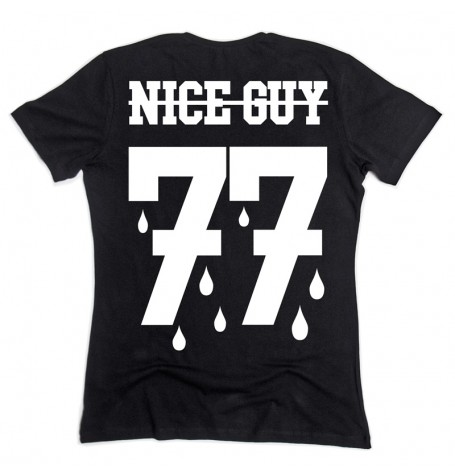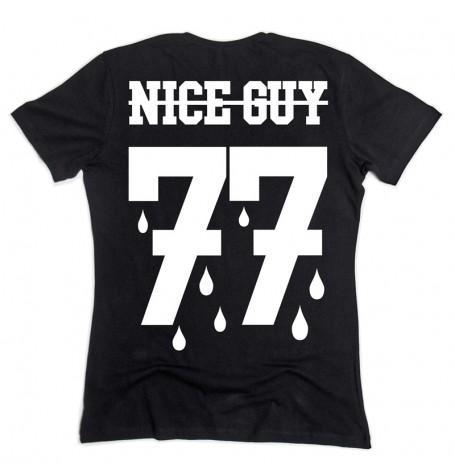
Welche Schrift ist das ?
Suche seit tagen den Font Nice Guy 77. Finde es aber nicht kann mir einer helfen ? :/
Ich glaube, Robert hat sie gefunden. Die Erstgenannte passt auffallend gut, nur E und G scheinen in der Mitte modifiziert (wegen der Durchstreichung?). Und die Sieben. Vielleicht wurde noch eine zusätzliche Kontur bzw. Versatz verwendet, siehe Innnenraum vom Y.